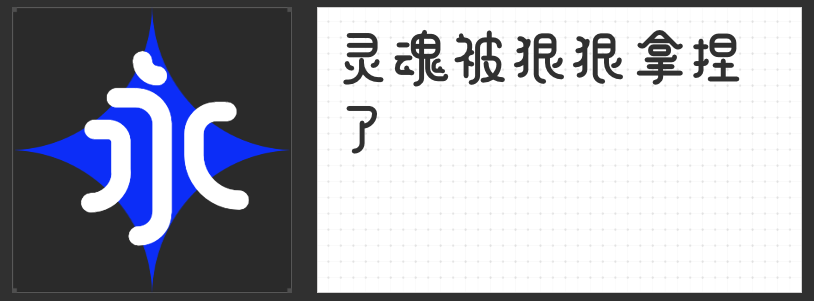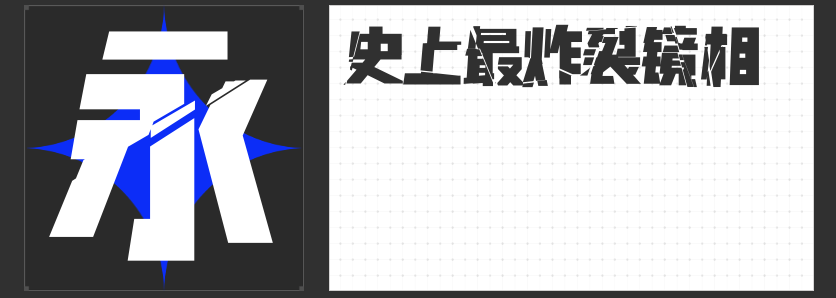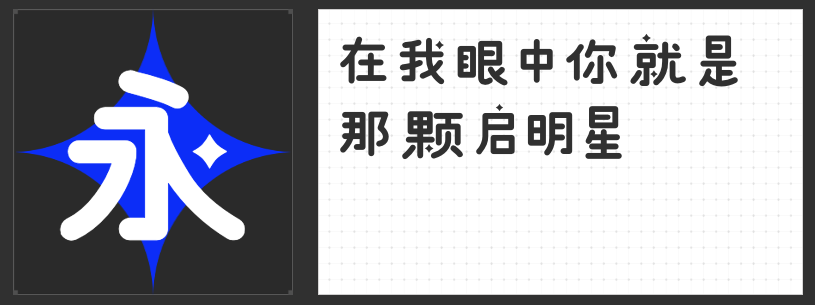
四款游戏创意字体:解锁奇幻世界的视觉密码
在游戏设计中,字体不仅是信息传递的载体,更是塑造世界观、强化氛围的核心元素。从萌系冒险到暗黑史诗,从科幻未来到奇幻魔法,一款契合主题的创意字体能瞬间点燃玩家的沉浸感。本文精选四款风格迥异的字体,为游戏开发者提供灵感与选择。
一、字恋狂丸粒简
以圆润为设计语言,这款字体通过笔画两端的圆角处理与“圆头圆尾”的造型,赋予文字独特的亲和力。其线条简洁流畅,无尖锐棱角,仿佛被温柔包裹的糖果,非常适合休闲益智、模拟经营类游戏。无论是儿童向的卡通界面,还是治愈系冒险的标题设计,它都能以软萌的视觉语言拉近与玩家的距离,传递轻松愉悦的氛围。
二、高手字斋哥特体Pro
灵感源自中世纪哥特式建筑与重金属文化,这款字体以尖锐的笔画末端、粗细对比强烈的线条,构建出阴森、庄重且充满压迫感的视觉效果。竖画如利刃,横折似铁链,整体风格冷峻而神秘,完美契合恐怖解谜、暗黑奇幻类游戏的需求。无论是吸血鬼城堡的牌匾,还是魔法咒语的符文,它都能以强烈的风格化设计强化游戏的沉浸体验。
三、励字多重人格简
借鉴影视中“人格分裂”的视觉表现,这款字体通过碎裂镜面的效果处理,将笔画拆解为不规则的几何碎片,形成错乱、炸裂的动态感。其独特的纹理设计使文字在排版时呈现层次丰富的视觉效果,仿佛文字本身正在经历一场精神风暴。适合悬疑推理、赛博朋克类游戏,用以表现角色内心的挣扎、虚拟世界的崩坏,或传递“打破常规”的叛逆态度。
四、高手兵克星耀体
以“星星”为设计核心,这款字体将点笔画替换为五角星形状,搭配圆润可爱的笔画线条,营造出既天真又充满幻想的视觉风格。其整体造型轻盈灵动,仿佛文字中跳跃着星光,非常适合童话冒险、科幻萌系类游戏。无论是星际旅行的标题,还是魔法学院的菜单,它都能以独特的创意元素为游戏世界增添一抹梦幻色彩。
从萌系治愈到暗黑压迫,从破碎冲击到奇幻童趣,这四款字体以多元化的设计语言,为游戏开发者提供了丰富的表达工具。选择与世界观契合的字体,不仅能提升视觉品质,更能通过细节传递情感,让玩家在踏入游戏的第一秒,便沉浸于精心构建的奇幻宇宙。